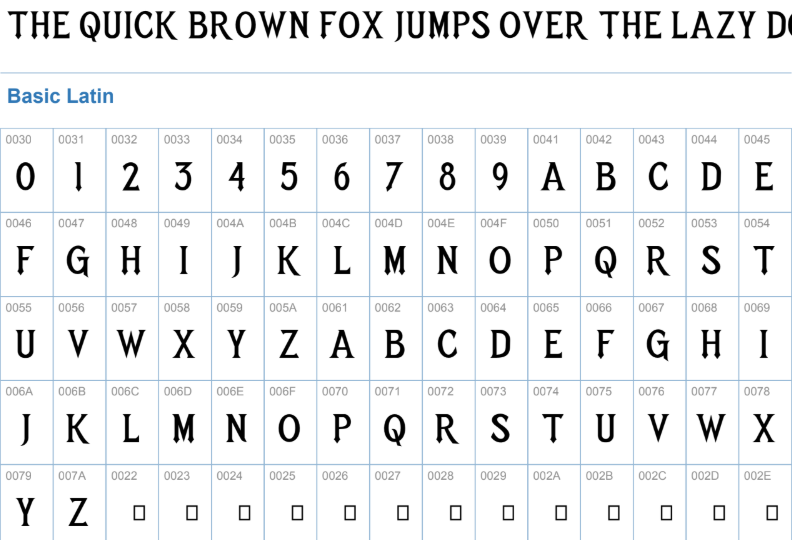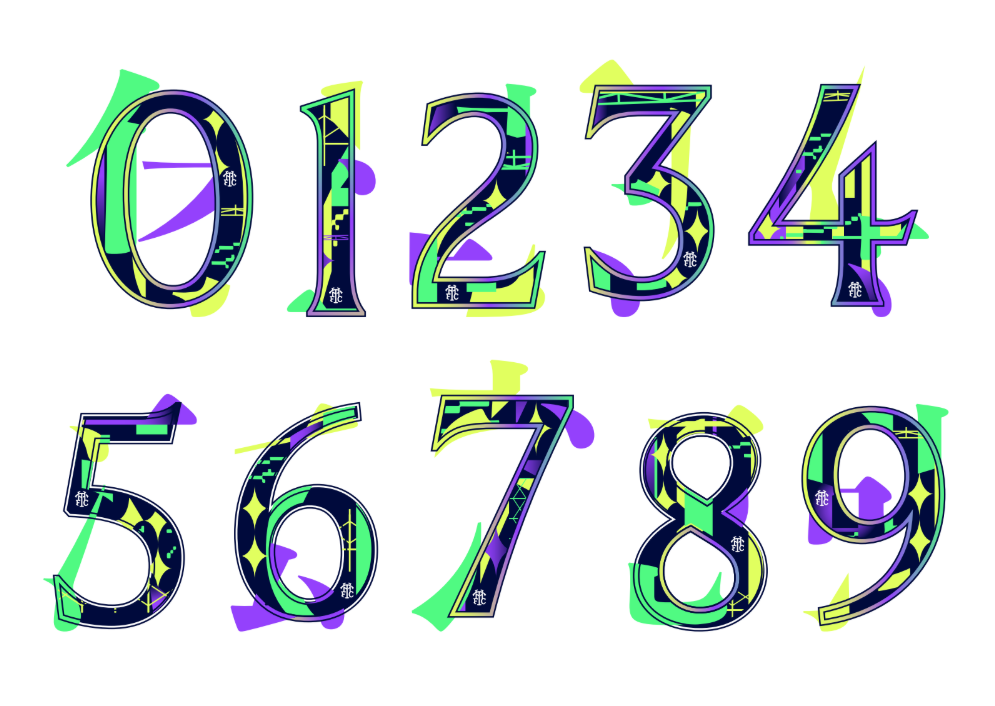
A camisa dos Red Devils carrega um peso histórico inigualável, e a cada nova temporada a parceria entre Manchester United e Adidas busca inovar mantendo a tradição de Old Trafford.
Neste post, trazemos para você a tipografia exclusiva utilizada pelo clube nas competições de Copas (FA Cup, Carabao Cup) e torneios da UEFA. Diferente da fonte padrão da Premier League, este design é uma criação exclusiva da marca das três listras, trazendo uma identidade única para o manto vermelho.
Estilo Visual e Aplicação
A fonte do Manchester United para a temporada 2025/2026 reflete a estética moderna e agressiva da Adidas. Com traços dinâmicos e cortes angulares, a tipografia foi desenhada para garantir leitura rápida e impactante nas costas dos jogadores.
Ela é ideal para a reprodução de camisas “Cup Kit” (usadas fora da liga nacional) e também se destaca em projetos de mockups esportivos, banners para redes sociais e personalização de brindes. A fonte mantém a consistência visual com os detalhes geométricos presentes na gola e nas mangas do uniforme oficial.
Dica de Uso: Para um acabamento perfeito em sublimação ou transfer, utilize o contorno (outline) na cor contrastante oficial (geralmente branco com contorno preto ou vice-versa, dependendo do kit).